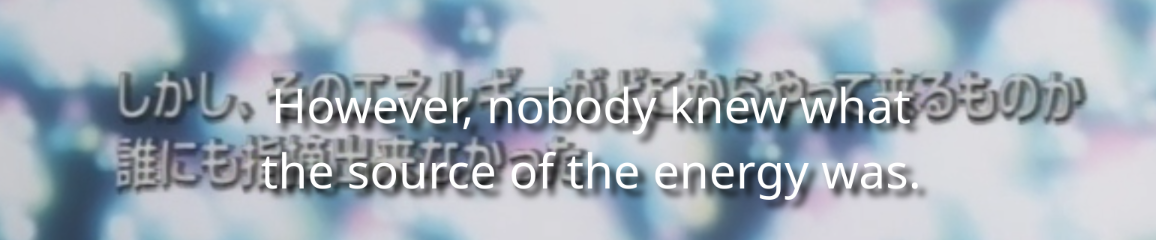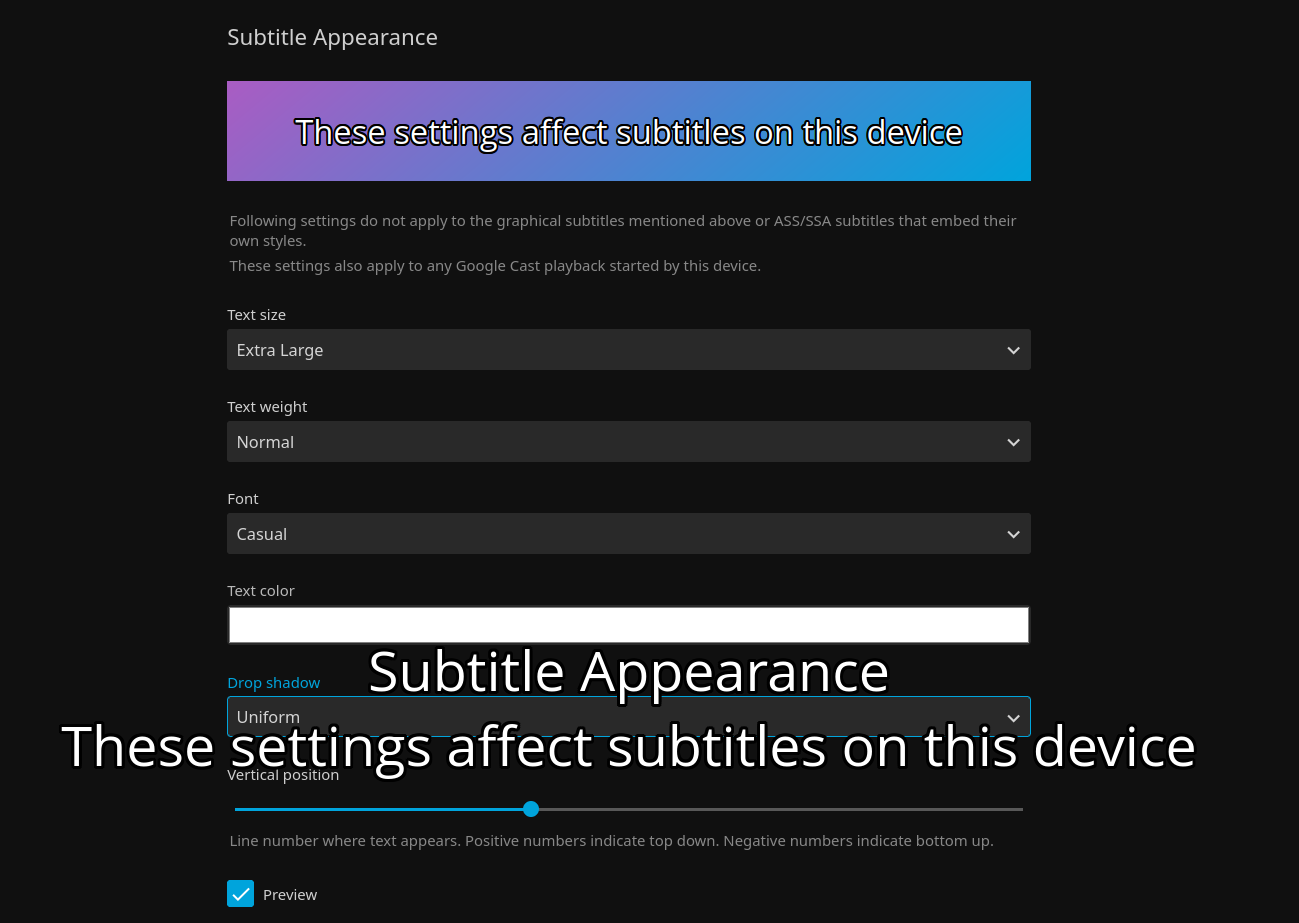
Jellyfin - Untertitel-Font, -stil und -schatten ändern?
ist euch ein Weg bekannt, wie man im Jellyfin Webplayer die Untertitelanzeige ändern kann?
Denn das hier ist irgendwie sch...ade. :(
Wer kam eigentlich auf die beknackte Idee, Schlagschatten statt Outlines zu verwenden?
+ das Problem, dass die Untertitel nicht weiß, sondern grau sind und man sie auf dunklem Hintergrund quasi nicht lesen kann.
Der Lösungsansatz mit den HDR Einstellungen brachte keine Besserung.